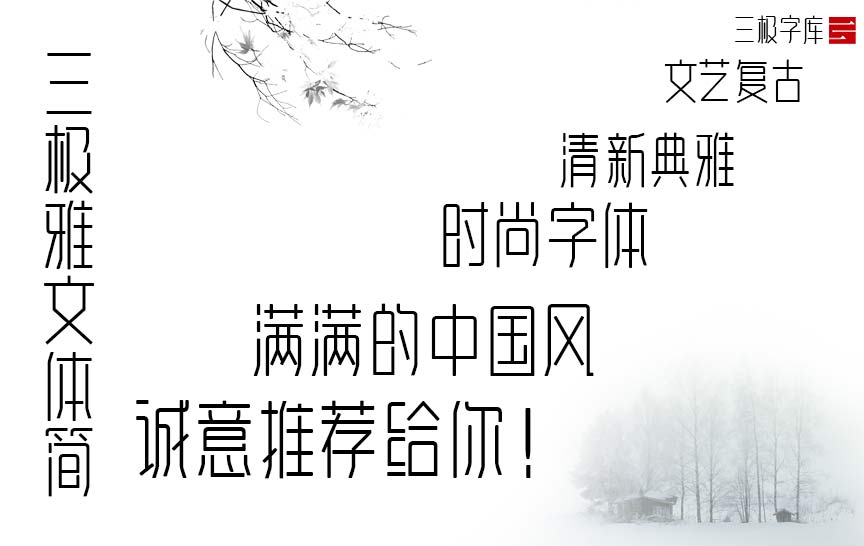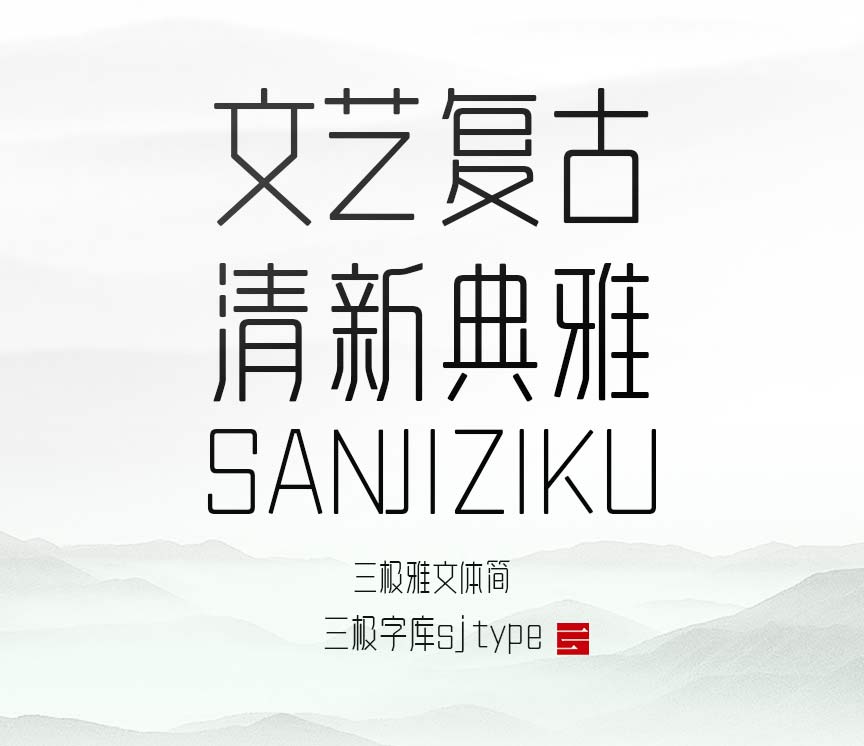
字体名称:三极雅文体简
设计师:曾南,欧伟
三极雅文体简是一款有着清新、文艺古典风的字体。这款字体的字面狭长,重心较高,用笔夸张,钩、捺特点明显。笔画镜像对称,折笔统一圆弧优雅,最大简化笔画形状,简洁时尚。字形清秀古朴、造型秀美惬意、点画呼应,新颖独特、纤细流畅。整体风格典雅质朴,秀丽端正艺术性较强。字形修长,简洁柔美,适用于文艺类广告和产品包装设计。
适用媒介:报纸、杂志、广告、标志、宣传册、包装、影视、屏幕显示、交互设计。